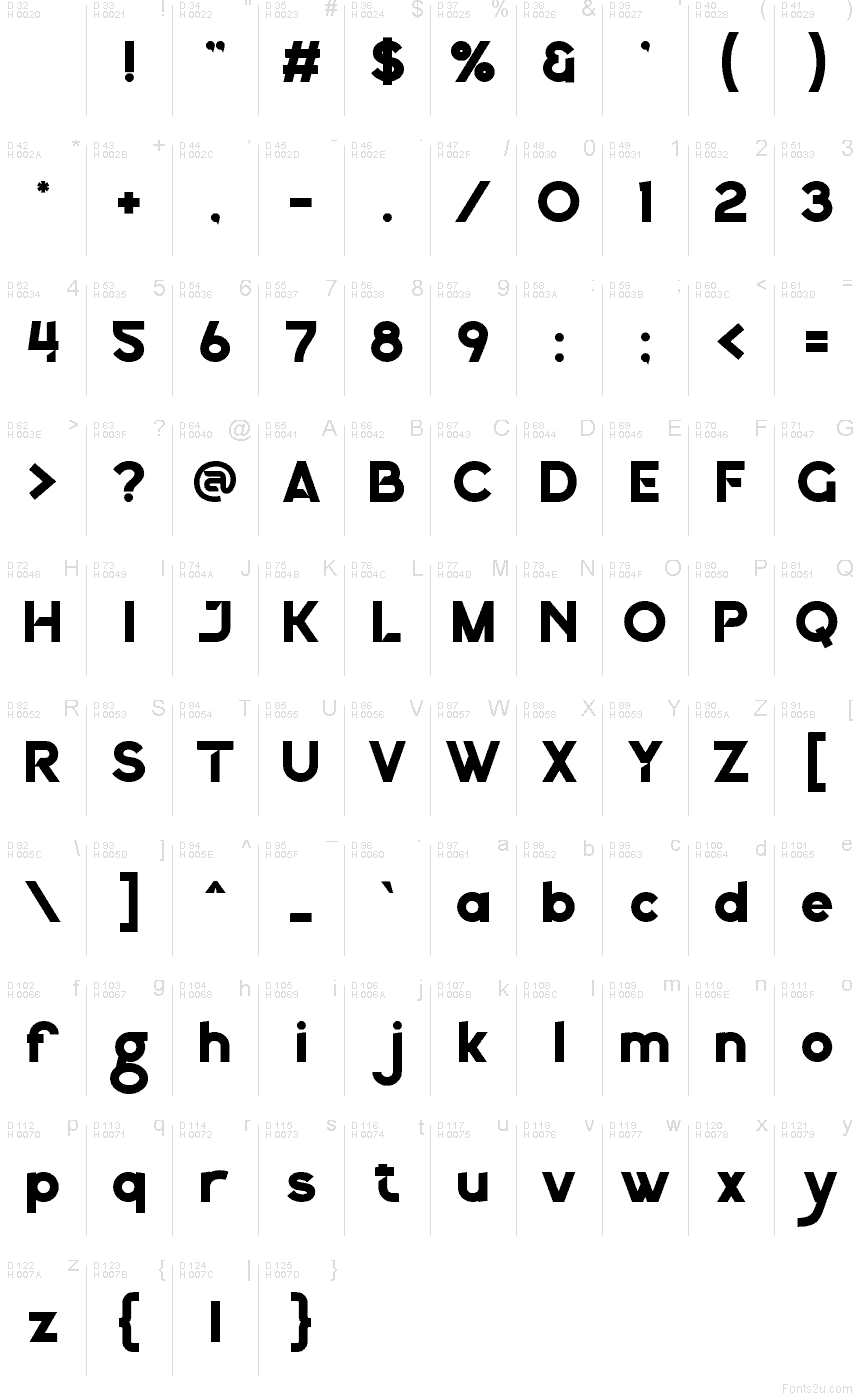
Rafhel, da Ermedia Studio, é uma fonte sem serifa geométrica gratuita, caracterizada por letras densas e pesadas com incisões diagonais nítidas. Curvas circulares e traços verticais largos compõem uma silhueta sólida, marcada por cortes angulares que se repetem ao longo de todos os caracteres.
Selos musicais independentes podem utilizar esse visual de papel recortado em capas de discos, cartazes de eventos e itens de merchandising, especialmente para lançamentos centrados em artes geométricas de forte impacto. Essa geometria segmentada combina perfeitamente com o público atraído pela música eletrônica experimental.